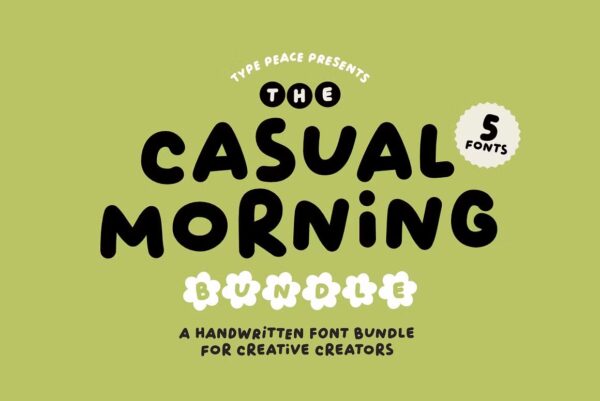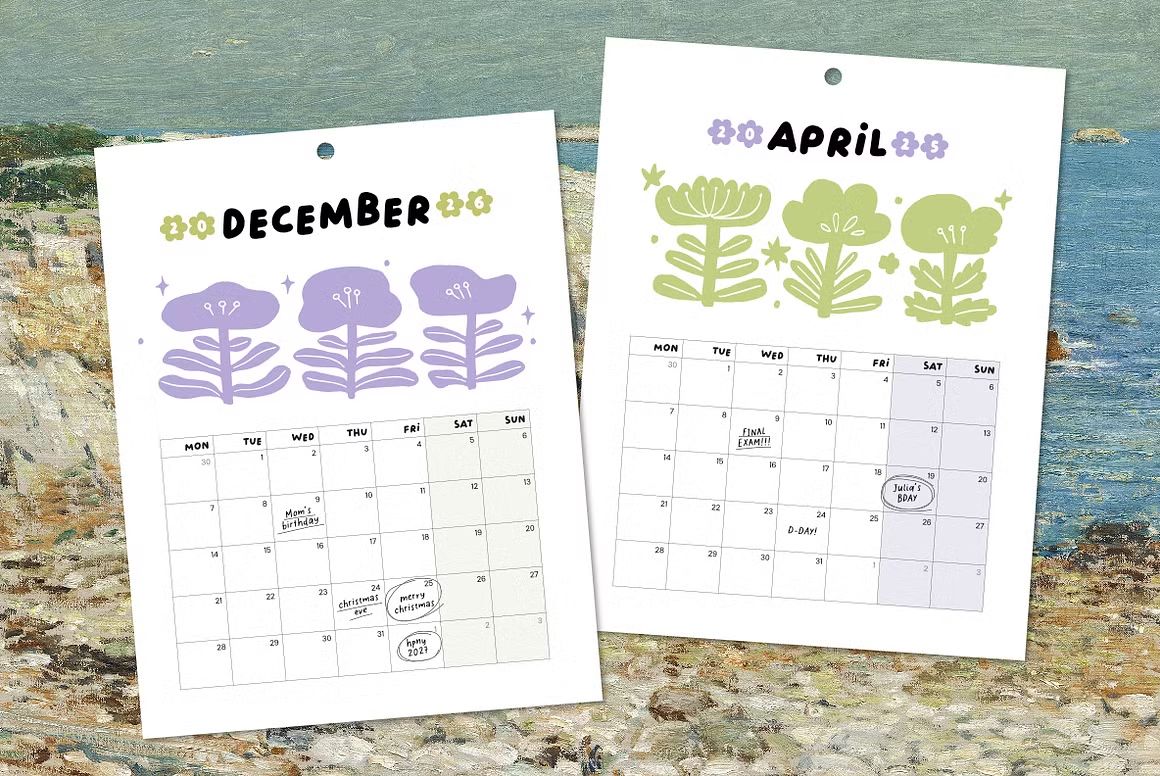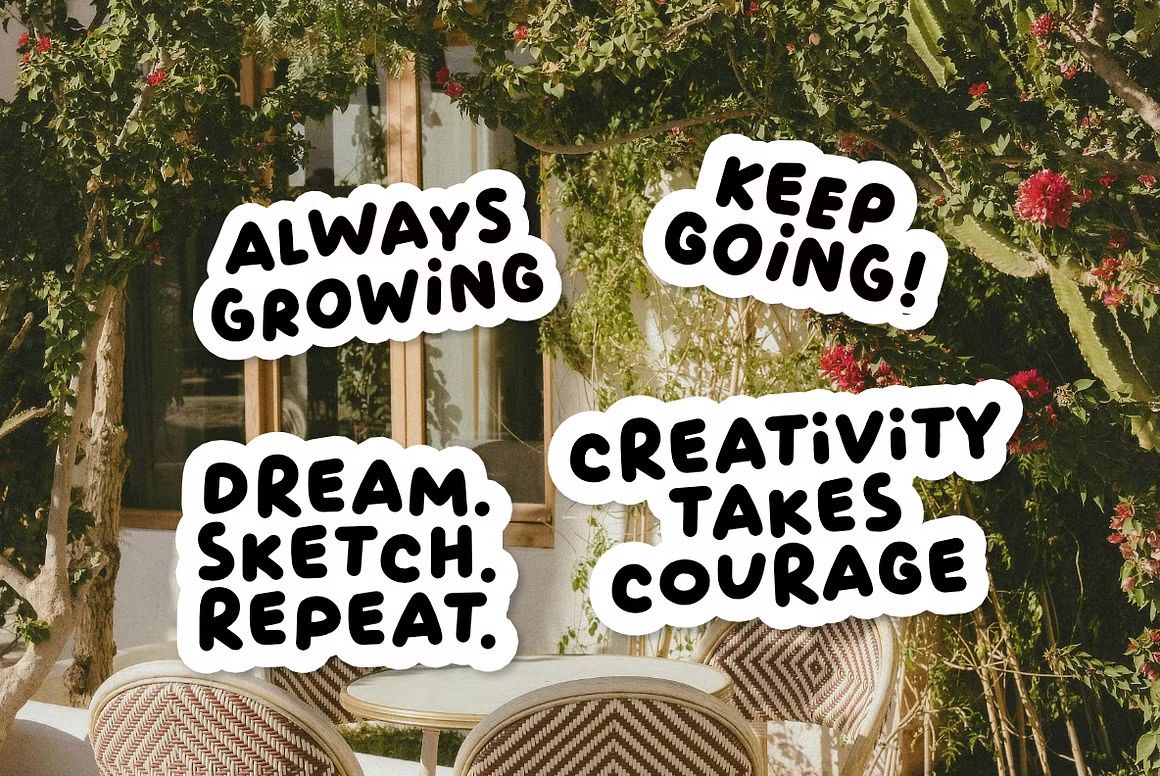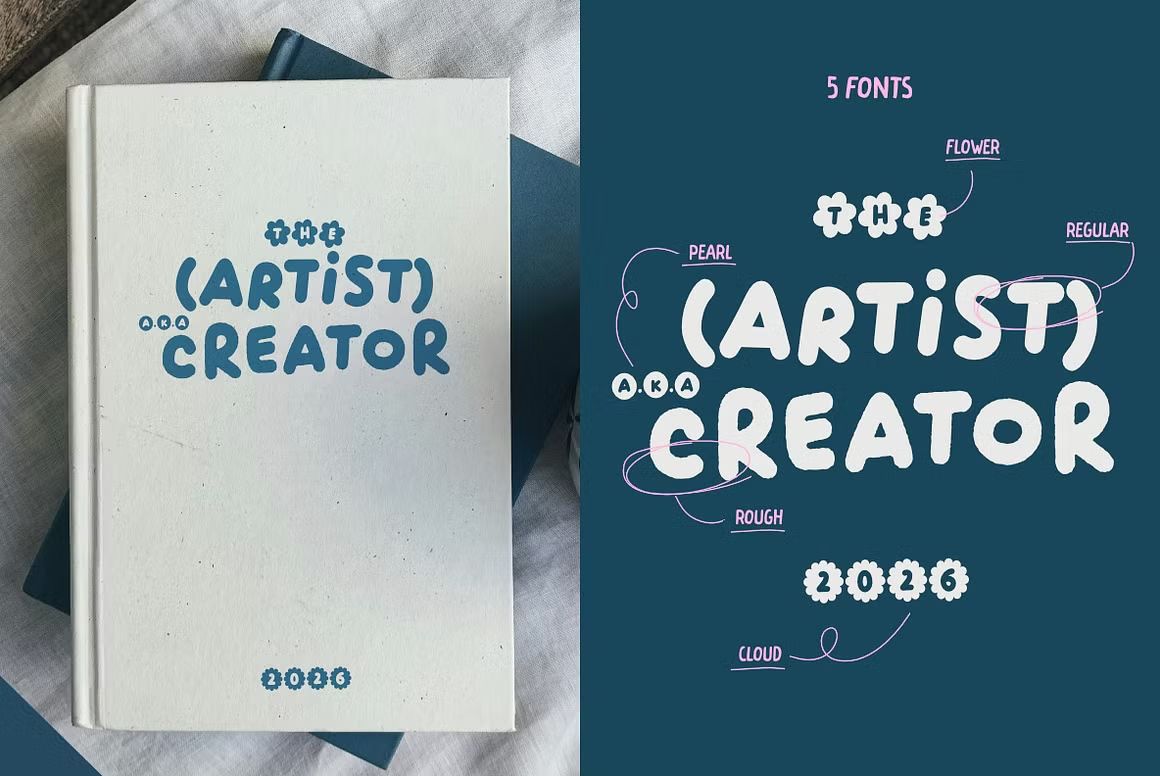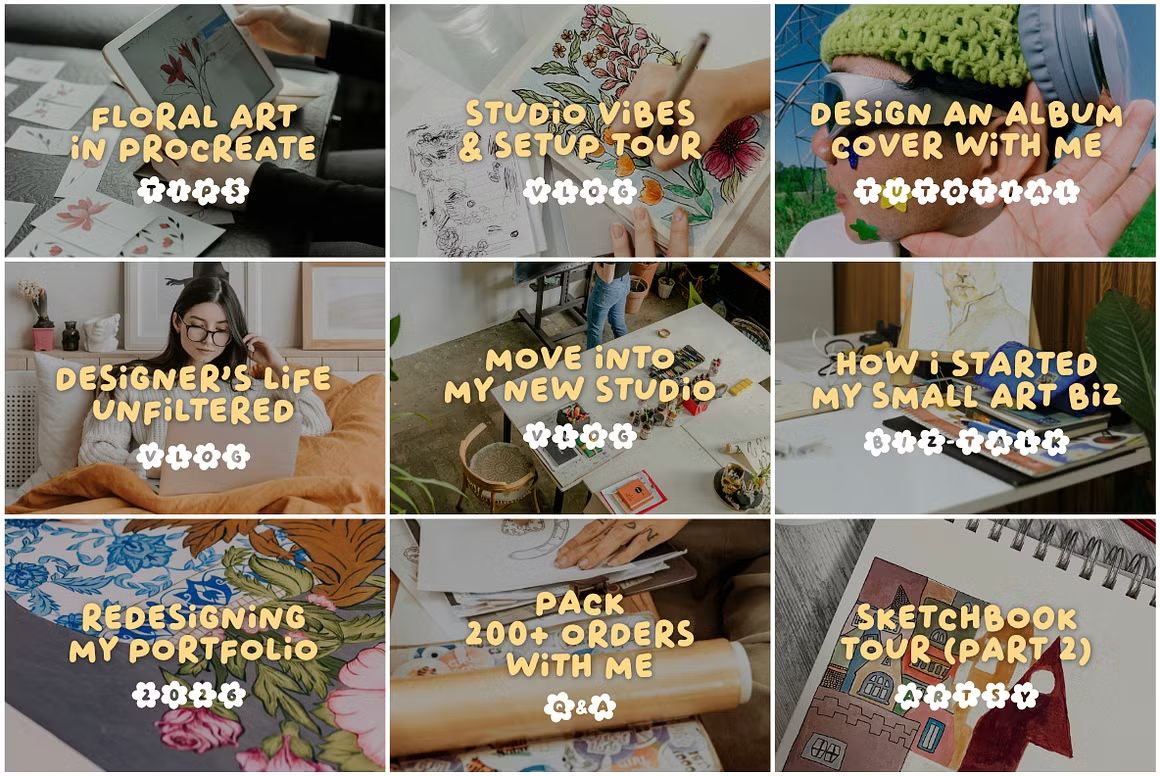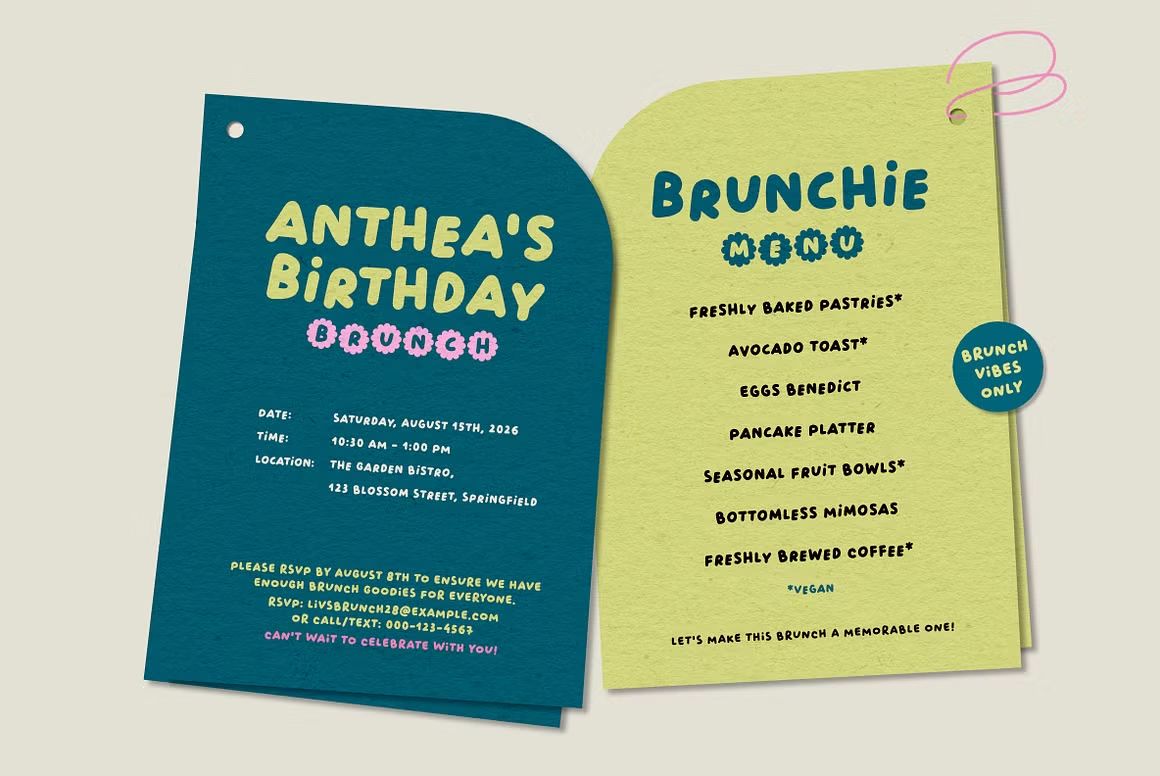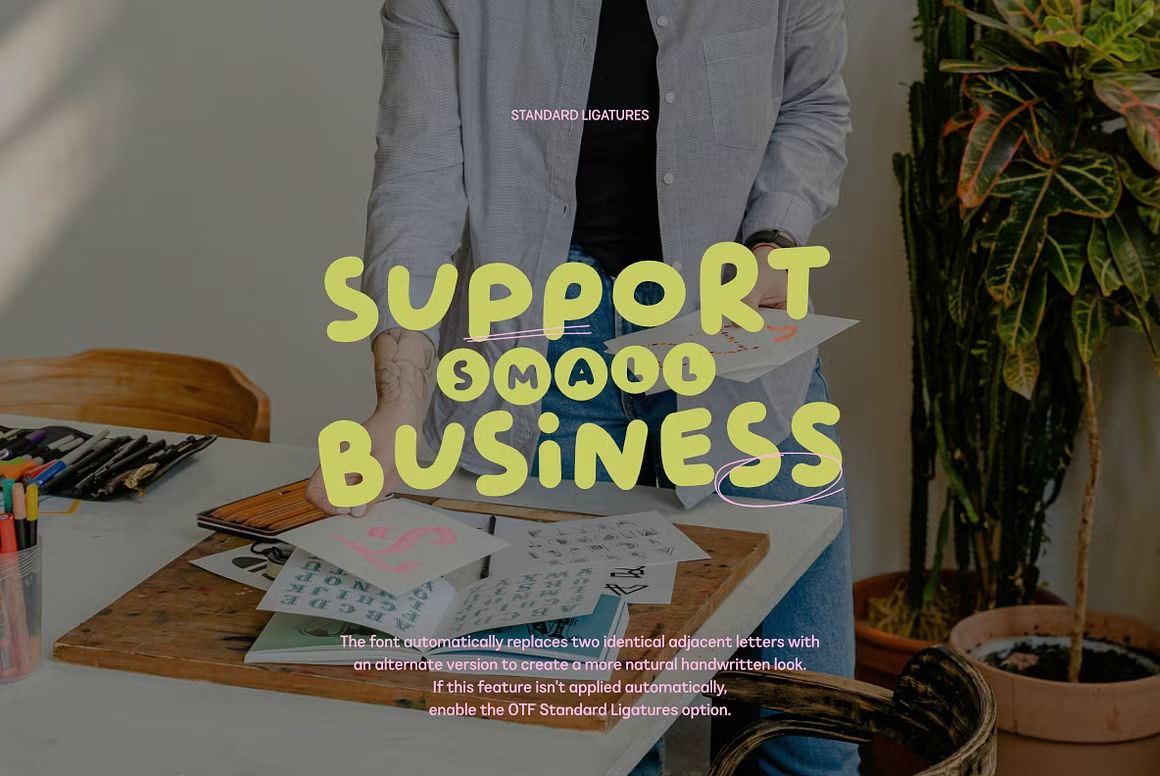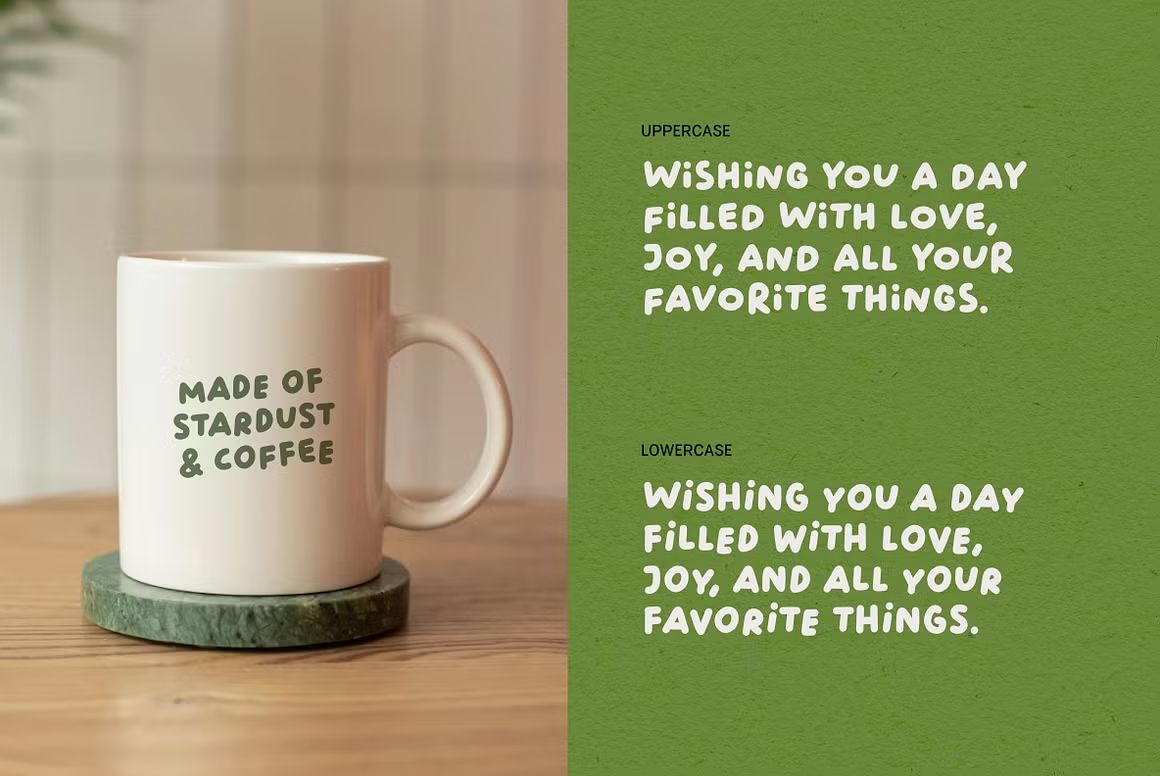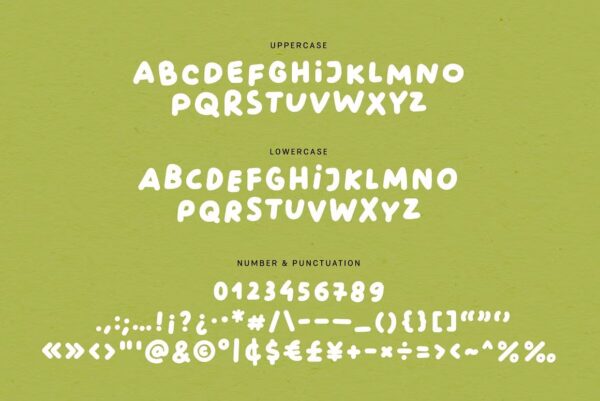
Casual Morning – Handwritten Font
Casual Morning adalah font handwritten santai dan natural, cocok untuk quotes, journaling, dan desain personal. Format OTF/TTF/WOFF, siap digunakan.
Casual Morning adalah font handwritten bergaya santai dan natural, menyerupai tulisan tangan sehari-hari yang hangat dan personal. Cocok untuk desain journaling, quotes, undangan informal, branding kreatif, dan konten media sosial. Gaya tulisannya yang ringan dan mudah dibaca membuatnya ideal untuk menciptakan nuansa yang ramah dan autentik.
• Handwritten font bergaya santai dan alami
• Ideal untuk journaling, quotes, dan desain personal
• Termasuk huruf besar, kecil, angka, dan simbol